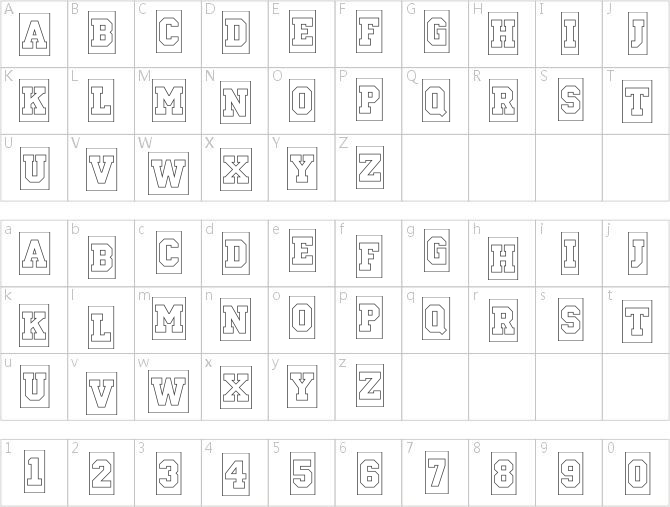
a_CampusCmOtl-Bold 詳情頁
a_CampusCmOtl-Bold字體字庫是一款讓人賞心悅目、百看不厭的英文字體,適合各類廣告和產(chǎn)品包裝設(shè)計應(yīng)用,字體大小0.07MB,格式為ttf字體,上傳用戶是1733150348,作者/版權(quán)方為未知